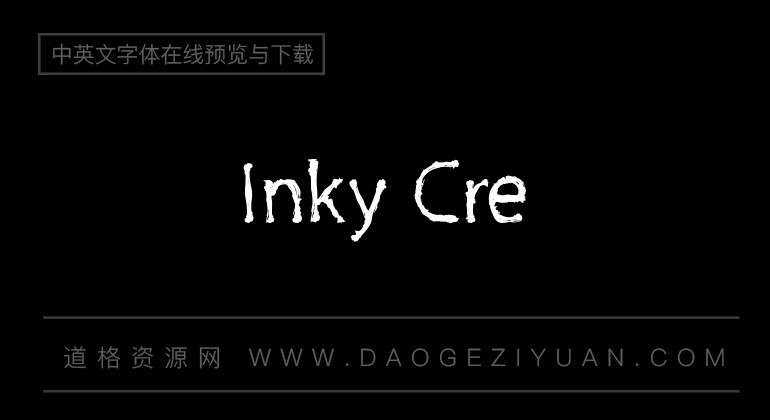
? Inky Cre 字体是一种简洁、有趣的字体,它的特点是有着细节丰富的线条,每个字母都有一个独特的外观,给人以清新、轻松的感觉。它的字体结构比较简单,可以清晰地展示出文本的内容,因此适合用于报刊、广告、标志等不同的印刷项目。内容介绍
Inky Cre是一款非常不错的手写艺术字体,具有很好的视觉感,适合于文化类的宣传设计、商业类品牌的广告和产品包装设计以及个性化文字排版等较多场景。